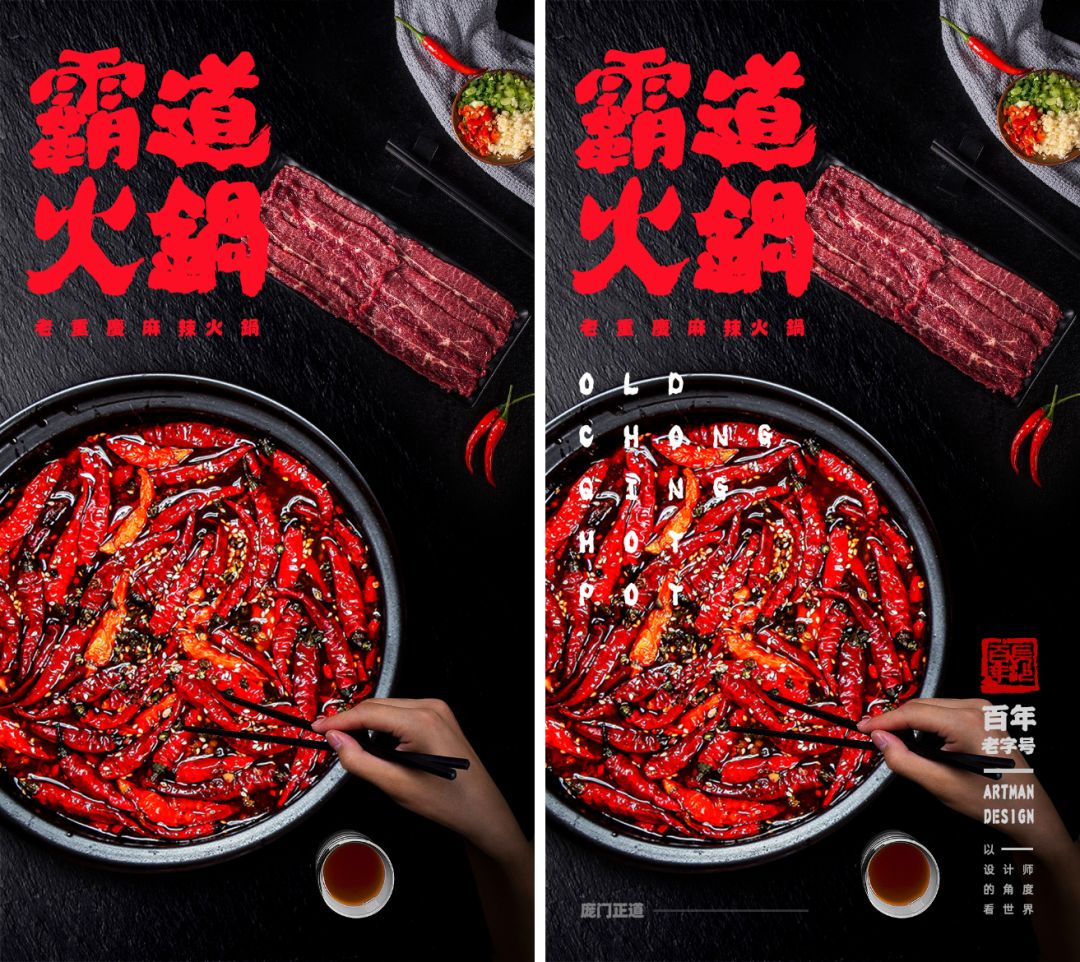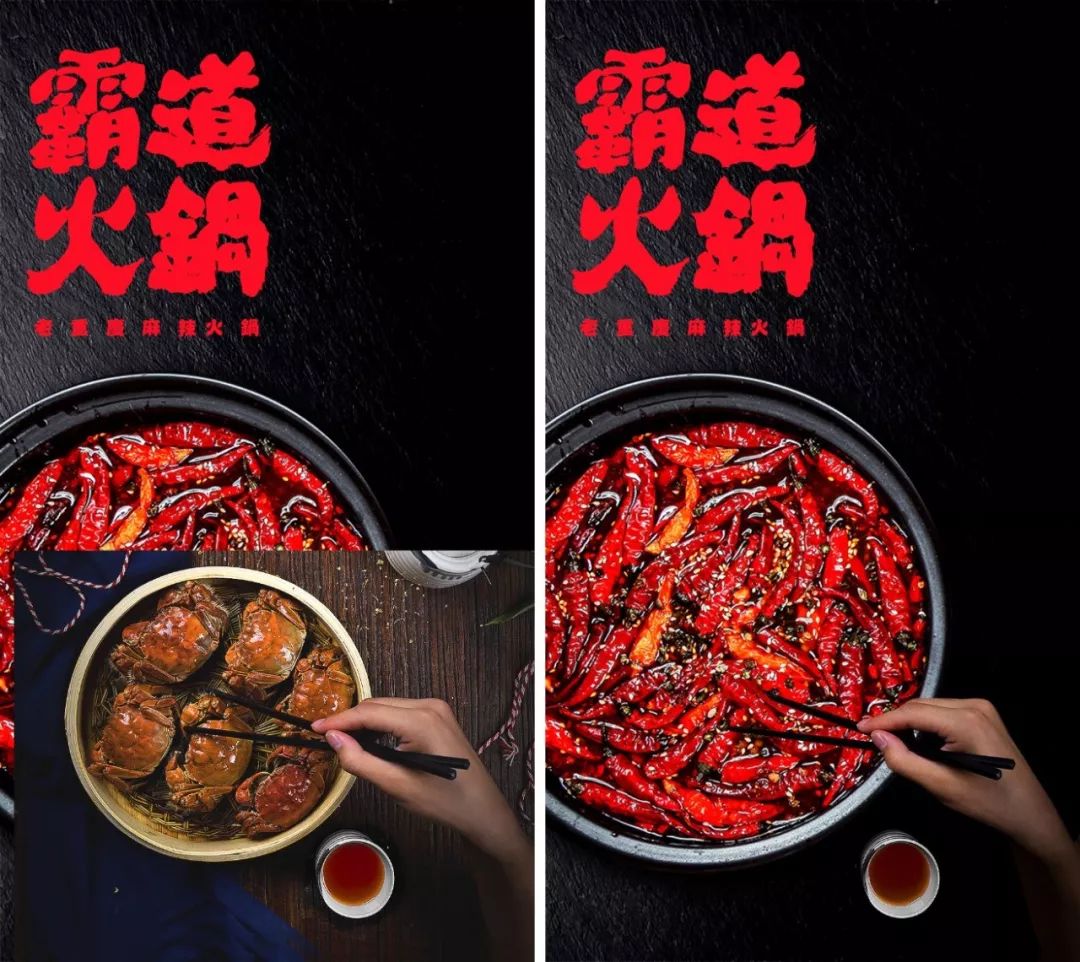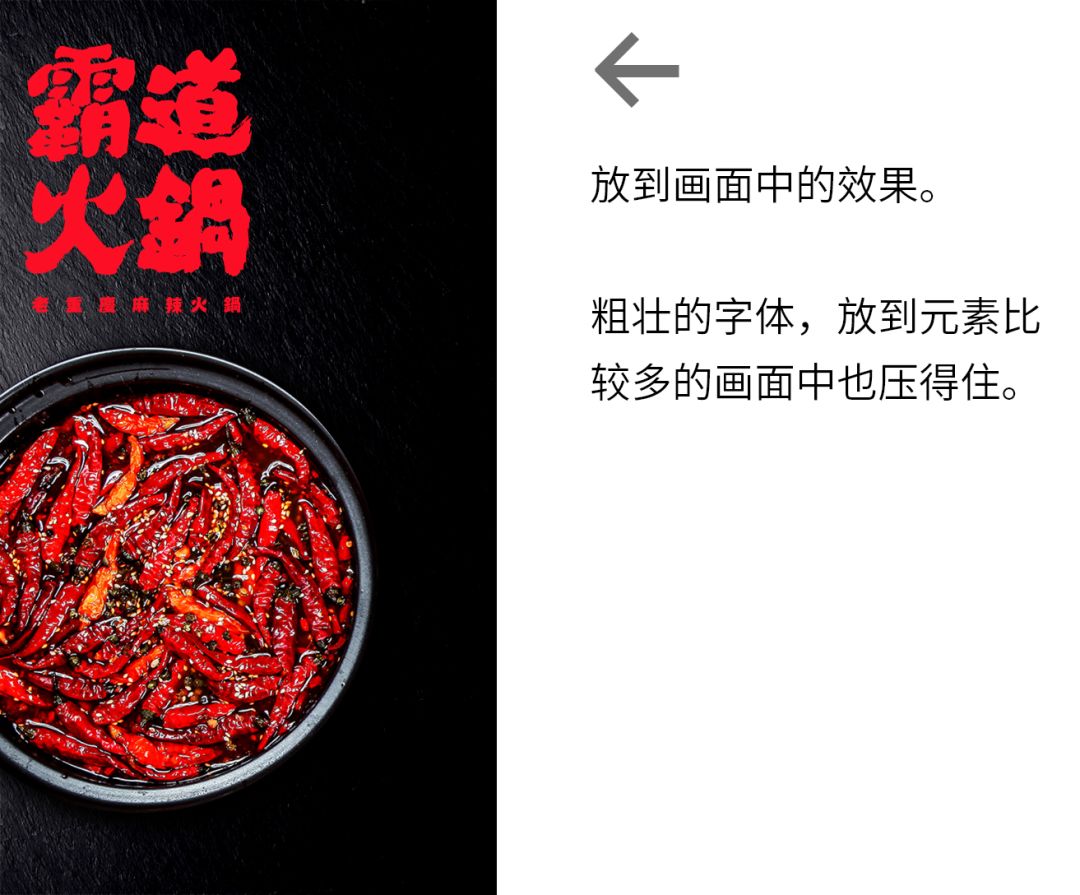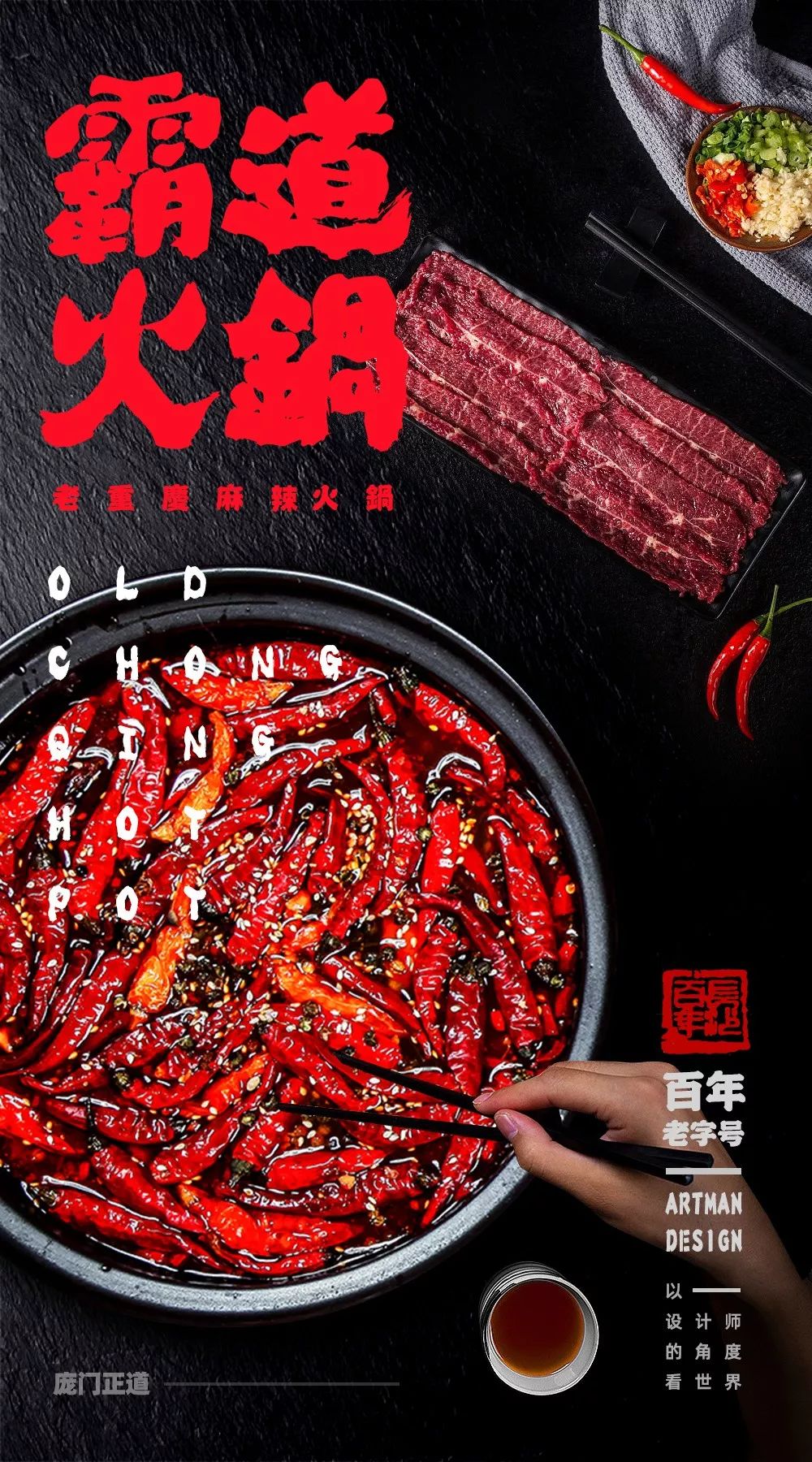
这样的整容式改稿,老板都看哭了!
上次做了一期改稿教程之后,发现大家还挺喜欢这种没有“水份”,上来就是干的教程。
既然这样的话,那当然是尽最大的努力满足大家的需求!
以后改稿定为一个固定的主题,不定期的会出一期改稿的教程。
惊不惊喜,意不意外?
另外,我希望大家在看改稿教程的时候,不要只关注修改后的对比效果,而是要更多的关注改稿思路。
毕竟,看我改,只是看个热闹。只有你自己改得好,那才是你自己的能力,对吧?
OK,
废话不多说,Just do it吧!
第一个案例来自于门友 @曹云鑫。
这是一个偏中国风的茶广告,用了大红的配色,再加上团圆的矢量画,烟花等中国元素。
画面整体比较清晰,干净。
不过问题是元素之间的拼凑感太强了,而且没有主体。
如下图所示,画面的三部分内容基本是等分的:
并且,这三部分的内容,在视觉上完全没产生联系,导致整个画面看起来就是不同的元素生硬的拼在一起。
像这种小广告用户都是一扫而过,所以一定要重点突出。
一秒钟不能看到重点,那就是失败的设计。
好了,接下来我们在保持画面风格不变的情况下,进行优化。
第一步,确立画面主体。
既然是茶的广告,那画面的主体必须是茶,并且占比要足够大,让用户一眼就知道这是一个茶广告。
第二步,优化一下主体的细节,再大概排版一下文案。
文案的处理上同样需要注意大小对比,将重要的信息突出,让用户迅速捕捉到重点。
接下来将其它信息安排好,促销的利益点可以采用小标签的形式展示。
最后,添加中国风的底纹,以及线框等元素丰富一下画面层次,就完工了!
很简单的几步,就将一个广告脱胎换骨了。
这里也没什么特别的诀窍,就是要抓住重点,少做无用的设计。
我们再来分析一下优化后的广告的信息层次:
是不是信息的主次就明确多了?
电商广告一定要遵守这样的规律:
商品 > 主文案 > 次要文案
用图形画出来就是这样的:
下次你做完一个电商广告之后,一定要想想是不是符合这个规律,如果不是,你要想清楚是有问题?
好了,最后看一下对比图:
只要掌握方法,改稿一点也不难啊是不是!
第二个案例来自于门友 @牧羊少年。
这是之前椰树广告的练习。细看一下这个广告,如果只从视觉来看,排版、字体、细节都问题不大,一切都中规中矩的。
不过我们一眼看过去,就会明显感觉这个广告不对。
那到底是哪里有问题呢?
不是设计的细节,而是整体的氛围。
椰汁给人的感觉应该是天然、健康的,而这个广告的采用的黑黄配色过于压抑,让人完全没有食欲。
如果整体风格错了,那当然是做多错多。
OK,下面就来进行优化。
椰汁的这个包装确实太丑,我保留他们原有的风格,简单的给重新画一个。
第一步,简单的勾勒一个瓶身。
为什么用这么亮的黄色?
因为椰汁是超市最靓的那条仔啊!只有亮黄色才配得上它!
第二步,将椰汁包装最精华的部分一比一复制过来,再加上瓶盖子,瓶身的明暗过度,就差不多定形了。
明黄色、黑色、红色、蓝色,将这些颜色撞在一起,确认过眼神,这就是原汁原味的椰树椰汁。
好了,
接下来处理背景。
为了体现椰汁的原生态,我选了一张大海与沙滩的图作为背景。
将背景高斯模糊一下,拉开与产品的距离,同时也可以使画面更加干净。然后在下面添加木板,这样产品就和大海形成了远近关系。
最后来添加椰树叶子,以及处理好光影细节:
这样,整个场景就完成了。
记住,设计元素不是越多越好,一定要恰到好处。
最后再添加文案:
这个画面中的椰汁,是不是看着就很有食欲了?
最后来个对比图:
全新的椰树style,
是不是很厉害的样子!
第三个案例来自于门友 @故里有长安。
作者用大红色来突出火锅的麻辣重口味,色彩上是没问题的。
画面处理细节上,问题比较多。
一、上下分割的方式有点生硬,上面的文案部分和下面的图片脱节了。
二、主文案的字体没有力度,“霸道火锅”一点也不霸道!
三、图片部分有点乱,主体不够突出。
切记,我们一定要围绕主体来做设计。
所以优化的第一步,也是先提取画面主体:
将原图中的火锅抠出来放大,当作画面主体。
因为火锅本身是红色的,所以我将背景改成黑色的,这样更能突出火锅的红辣。再添加一张石头质感的背景,画面一下就有了厚重感。
第二步,字体选择。
原图中的字体太细,太没力道了,跟火锅的重口味调性不符,因此我换了一款更粗壮,更个性的书法字体。这样看着更有品牌感。
为了让这口锅看起来更霸气一些,我们可以添加一些小素材,来衬托它的“大”。
比如说一只拿着筷子的手:
加了这只手之后,不但可以显得锅很大,而且也让整个版式形成了变化。
再添加一些辣椒,蘸料之类的元素来丰富画面:
最后,加上一些细节文案之类的,就大功告成了!
高清大图来一波:
对比图:
写着写着,肚子有点饿。。。
第四个案例来自于门友 @青铜的崔。
这张海报的亮点在于作者做了一个N2的创意,呼应主题中的氮气。
存在的问题也比较多。
首先是颜色。
背景是天空,不过在蓝色中混入了一些灰色的云,显得太脏了,再加上同样有点脏的轮胎,整个画面显得比较旧,看起来不太舒服。
其次是画面主体和背景之间并没有形成呼应关系,轮胎和背景的天空完全是格格不入。
因此,我们的优化方向就从主体与背景的融合切入。
第一步,原图的轮胎有点脏和旧,需要先处理一下。
通过加大对比度,色相调整,让整个轮胎的颜色统一成深蓝色,这样看起来就干净了很多。
最右边的大轮胎我还加了一个旋转滤镜,这样可以让它更加的动感一些。
好了,接下来再看背景处理。
轮胎一般出现的场景是修车场,所以我找了一张类似汽车修理工厂的背景。
再调整一下色相,就完美融合了!
一番操作之后,图形部分就差不多了,接下来再将文案部分排版好。
看下高清大图:
对比图:
效果很不错吧?
还是一个轮胎练习的案例。
这张海报整体上还是比较清爽的,重点信息突出,排版也算工整。
它的问题是画面的层次感比较弱,一眼看过去,GET不到画面重点,信息传达的效率很差。
另外,文字部分占画面的比例太大,看上去满屏全是字,让人不想看下去。
弄清楚问题所在,接下来就看如何优化吧!
第一步,确认画面的主体,将轮胎移到画面中间。
我想保持画面原有清爽的感觉,因此找了一个水波的素材,让轮胎的下半部分浸入水中。
第二步,处理轮胎和水的融合。
轮胎的下半部分作模糊处理,在色调上也要偏冷色,模拟出水中透视的感觉。
第三步,处理文案。
先简单的把文案理一下,大致分一下层次。再提取文案中的重要信息,视觉上作突出处理。
经过一番优化后,得到右边的最终效果。
对文案排版来说,最重要的原则就是简洁,清晰,重点突出。
好了,
高清大图走一波:
对比图:
从信息传达的角度看,改完之后是不是清晰了很多?
围观完一大波案例,
有没有神清气爽的感觉?
好了,这期的改稿内容就到这,
接下来到了你动手的时候了。